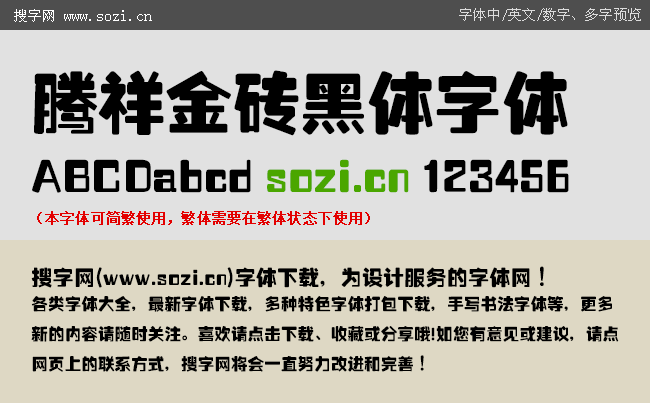
金磚黑體字體
搜字網(wǎng)給大家提供一款黑體藝術(shù)字金磚黑體字體下載。金磚黑體字體是一款風(fēng)格非常獨(dú)特的黑體字體,它的字體造型是重上輕下、厚左薄右,全部筆畫均以方筆展現(xiàn),具有非常明顯的特點(diǎn)。適合畫冊(cè)、海報(bào)、宣傳標(biāo)題等場(chǎng)合使用。